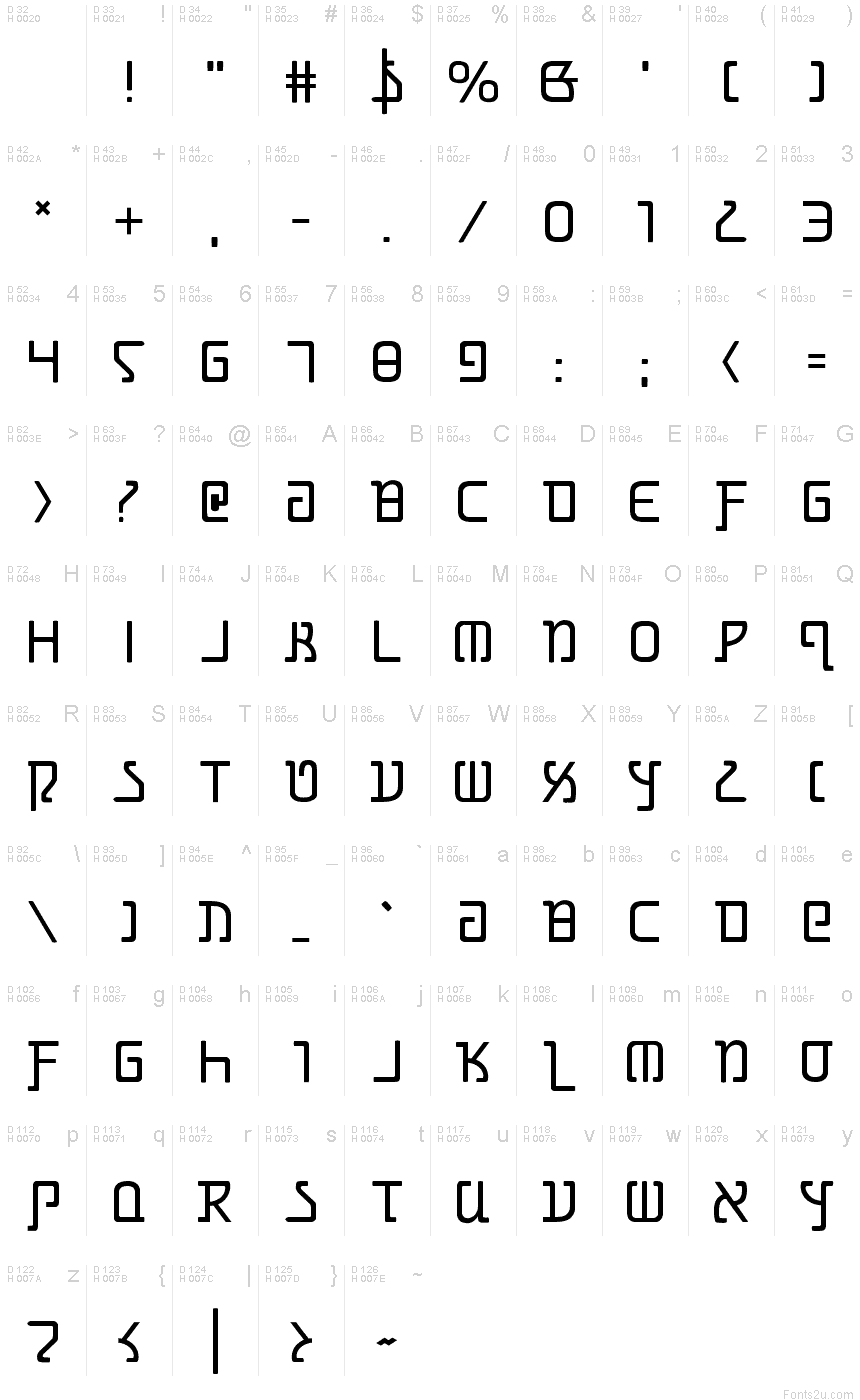
Grimlord od Iconian Fonts to darmowy retrofuturystyczny krój pism display składający się z samych wielkich liter, zbudowany z wysokich, kanciastych form i w większości jednolitych linii. Zaokrąglone rogi łagodzą surową geometrię, a kilka liter wykorzystuje przycięte łączenia lub otwarte partie, które przypominają wczesną grafikę komputerową.
Projektanci pracujący w obszarze science fiction, kultury salonów gier czy muzyki elektronicznej uznają go za odpowiedni na tytuły gier, okładki płyt i plakaty wydarzeń. Jego mechaniczny rysunek może również kształtować branding technologiczny lub gadżety. Należy on zdecydowanie do vintagowego futuryzmu opartego na ekranach.